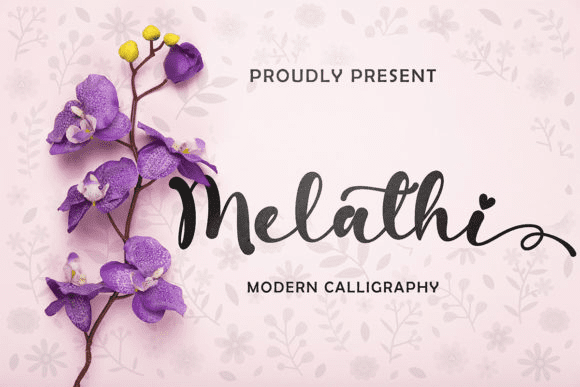
Название: Melathi Font
Мелати - это романтичный и сладкий каллиграфический шрифт с иероглифами, которые танцуют вдоль основы.
Он добавит роскошной искры любому дизайнерскому проекту, который вы захотите создать!